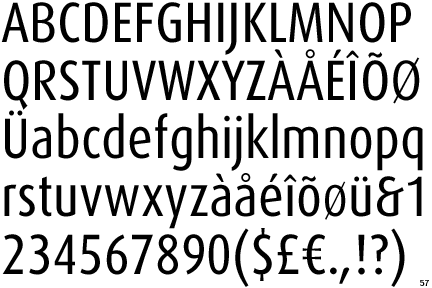
Hörgeräte Welche Schrift?
ich möchte für einen Bekanten ein Briefbogen gestalten.
Ein Logo hat er schon.
Ich kenne leider die Schrift nich, die dort benuzt worden ist.
Könnt Ihr mir vieleicht weiter helfen?
ja, das ist sie. Wobei die OT und die Pro bei der Condensed Light ein klein wenig dünner ausfallen als bei der "alten" (wenn mich meine Erinnerung da nicht komplett trügt, ich kann es selbst grad nicht verifizieren).